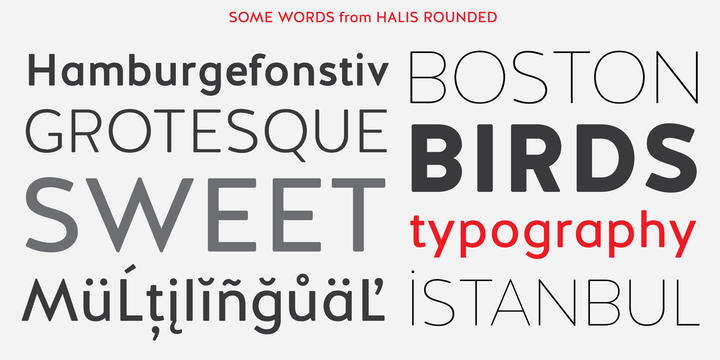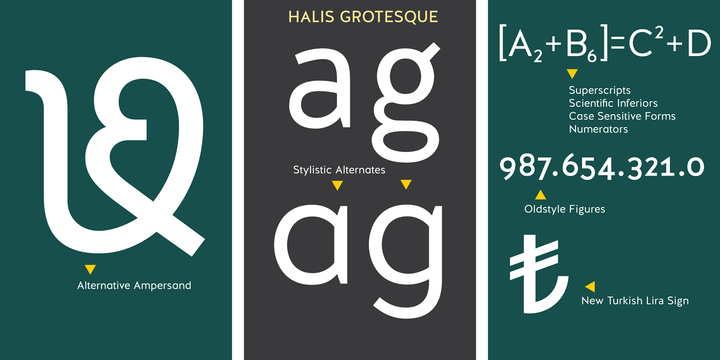
Halis Grotesque
Halis Grotesque font ailesi, Prof. Dr. Halis BİÇER'in tasarladığı ve benim yorumladığım türkçe ampersand içerir.. Ayrıca bu font çalışmam Myfonts sitesinde uzun zaman best seller listesinde kalmış, ve her ay yayınlanan myfonts bülteninde rising star olmuştur